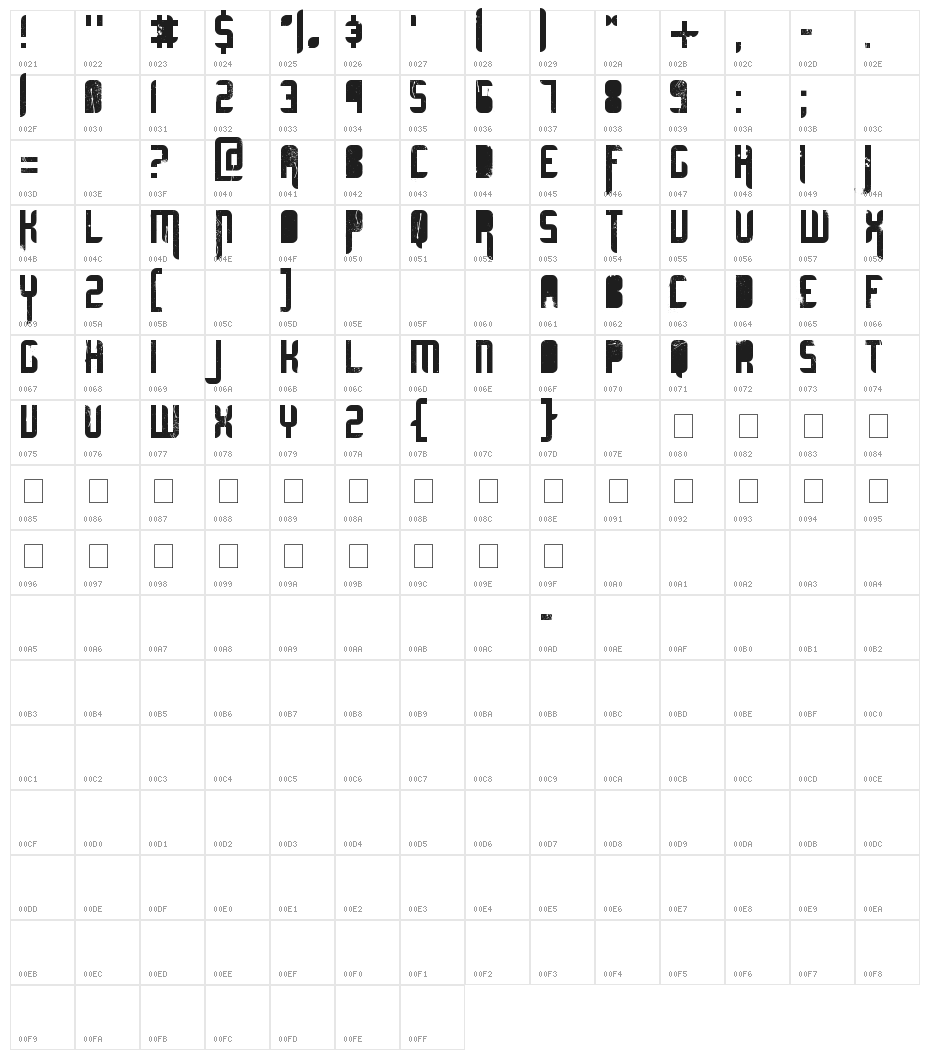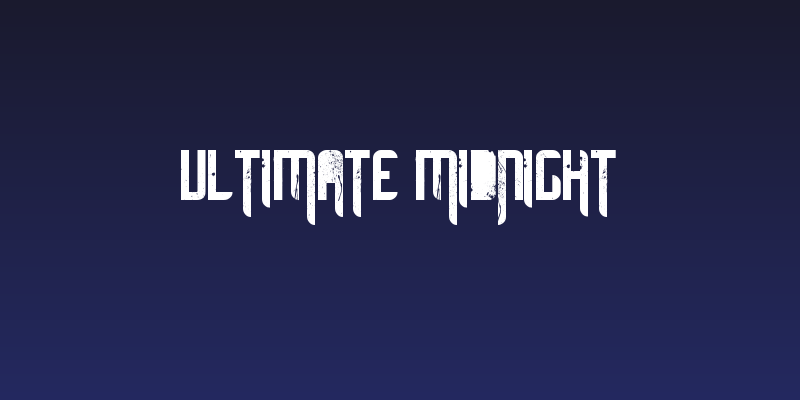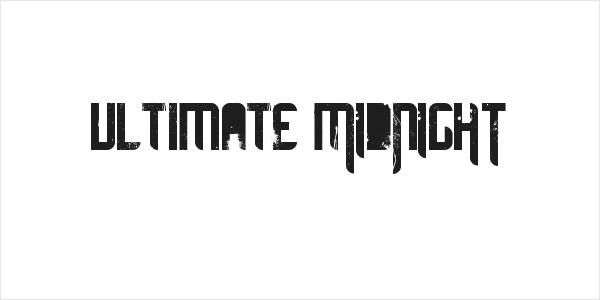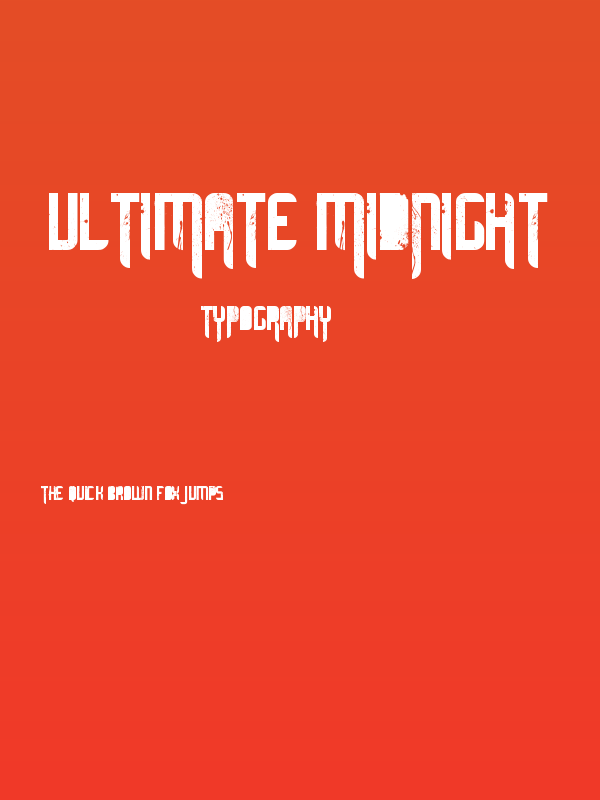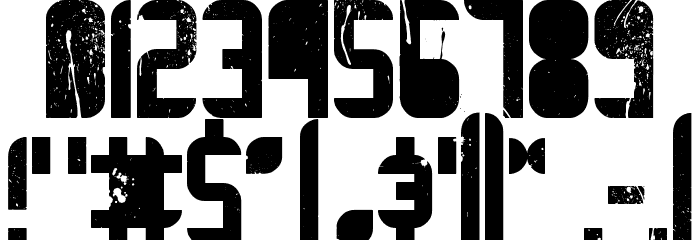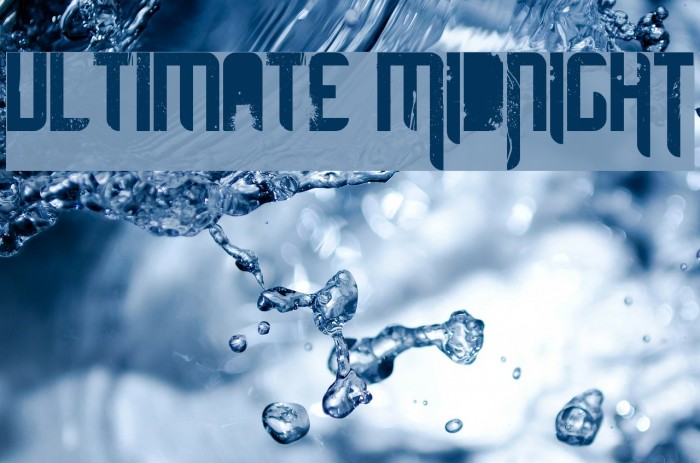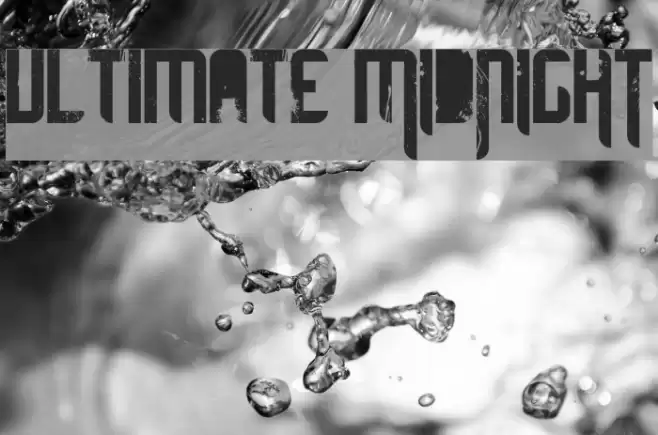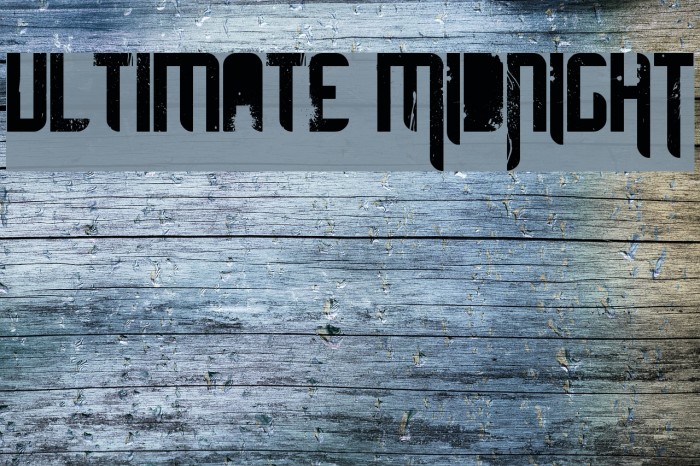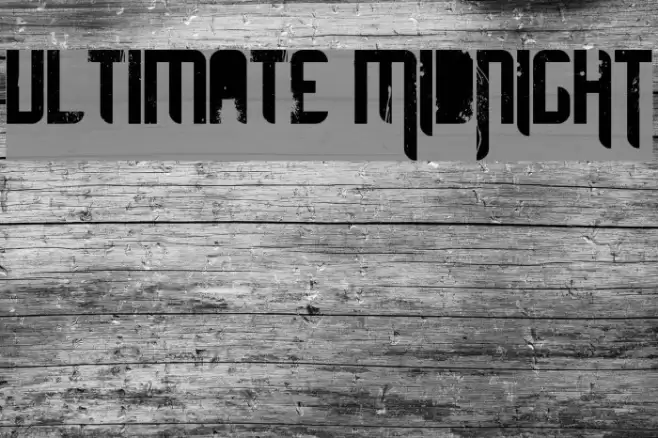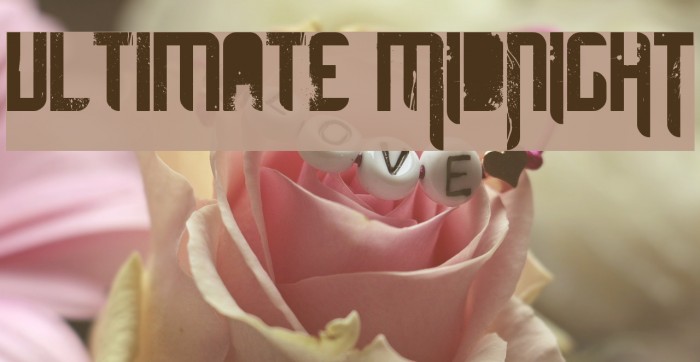
ultimate MIDNIGHT Font
✎ Distorted Eroded
| श्रेणियाँ | Distorted Eroded |
| समग्र शैली | Vintage, Industrial, Grunge |
| उपयोग का मामला | Headlines, Logos, Posters |
| सुझाए गए प्रोजेक्ट | Ideal for album covers, posters, branding for edgy products, or any design needing a vintage, industrial feel. |